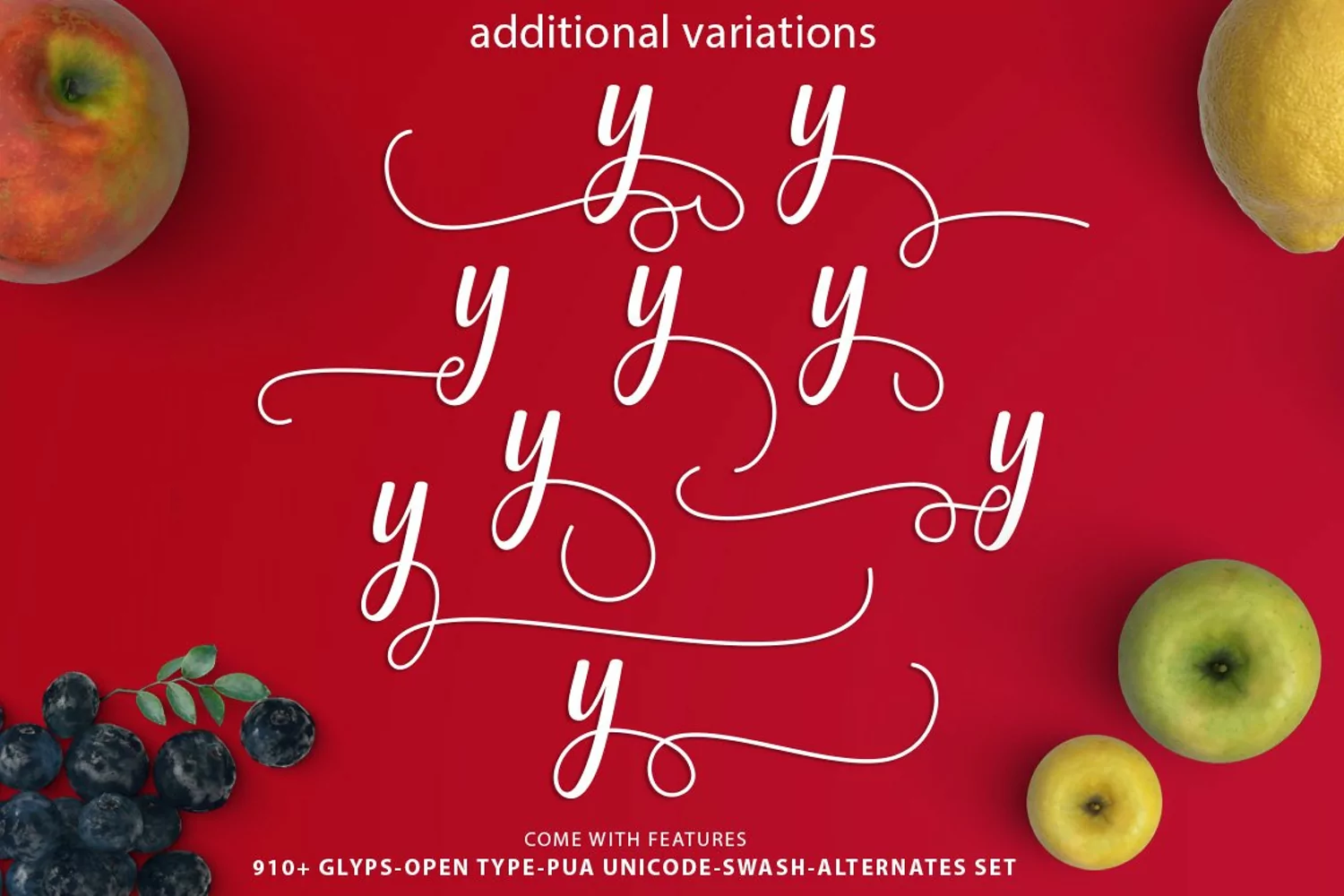
Julliyus Script
Memperkenalkan Julliyus Script kaligrafi tangan baru berhuruf tipografi naskah kaligrafi modern, yang menggabungkan gaya font klasik dengan modern
gaya kaligrafi
Ada lebih dari 910 mesin terbang di font termasuk set gaya, Kontekstual Pengganti dll fitur OpenType dengan Stylistic wakilnya,
Kontekstual alternatif beberapa karakter yang memungkinkan Anda untuk mencampur dan pasang mencocokkan huruf sesuai dengan desain Anda. Untuk mengakses mesin terbang alternatif, Anda
Dapat digunakan untuk berbagai keperluan seperti judul, tanda tangan, logo, undangan pernikahan, t-shirt, kop surat, signage, label, buletin, poster,
lencana dll